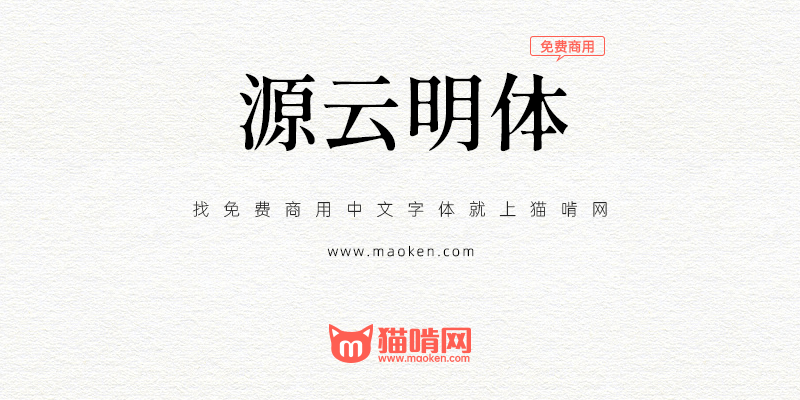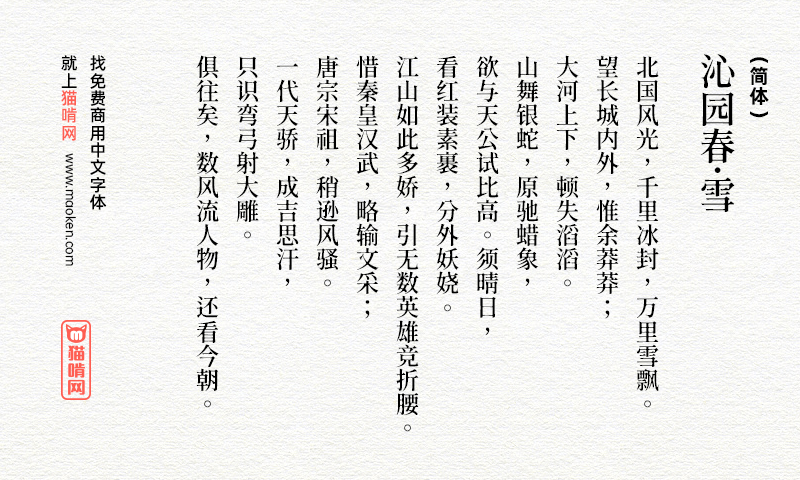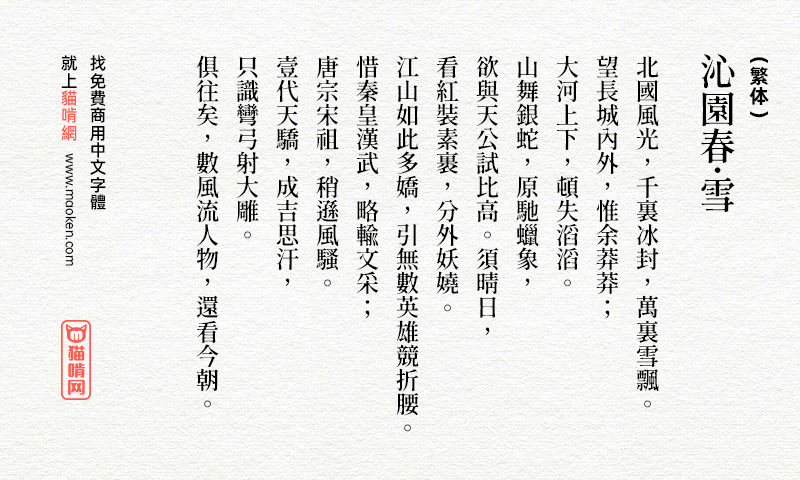
源云明体:怀旧而带点感性的思源系宋体字型
字体作者:But Ko (中国台湾) 字体字重:5个
台湾最活跃的字型社团「字嗨」管理员 But Ko 释出三款改造自思源宋体的繁体中文字型,开放让需要的使用者免费下载!分别为:源样明体、源流明体源云明体,不过目前仍在公测阶段,不排除未来有大幅更改规格的可能性。无论如何,可以从 GitHub 页面下载使用,将测试结果反映给开发者。
字体特色
「源云明体」是基于 「 思源宋体 」 的而改造的开放原始码中文字型。「源云明体」在横笔的起笔及竖笔的起笔、收笔处加入粗细变化,笔画交叉处有朦胧处理,使字体怀旧而带点感性。该字形提供Light、Regular、Medium、SemiBold等4个字重,能广泛运用在多种情境。字型改造虽以电脑程序自动进行,但在一些细节调整后可以明显感受出不同效果。
汉字不缺字
「源云明体」保留「思源宋体」所支持之所有汉字(包或日、韩文汉字与简体字),一般会用到的汉字几乎不会有缺字问题。 同时也保留了所有日文假名。(但删除了高达1万字的韩文字,有效降低字体文档的大小)
• 中文月、丹版,人工重否定百字常用字的写法,让写法世界统一。
• 新增KS X 1001编码范围内的韩文音节2350字与相容字母(输入法显示用)。
• 提供传统粗体模式,让软体的B按钮生效。(实作上是新增X版本,内容与B相同,附属于B版本的ttc文件中一并安装,作为R版本的粗体。otf版本未提供)
• 中文分为现代通用写法的月版(TW)与传统铅字写法的丹(TC)版,标点改回等宽。
• 日文版分割等宽版本(JP)与比例宽版本(PJP)。
• 新增jf7000当务字集与HKSCS2001汉字。
• 修复一些内的累积问题,如直排时破折号无置中、缺少白话字大写ᴺ。
• 支持台客语汉字
• 支持台客族语罗马拼音
• 提高注音符号品质,并支持注音直排格式
• 假名与关注类横排时比例宽
• 修改数字2、3、问号为较习惯的形式
• 修改部分KR版本不理想的文字对应,并统一各自文字的部件。
• 字型风格更加精致化。(三角形椭圆更圆一点。本来只有竖笔有的起笔加强,撇画也加上了。)